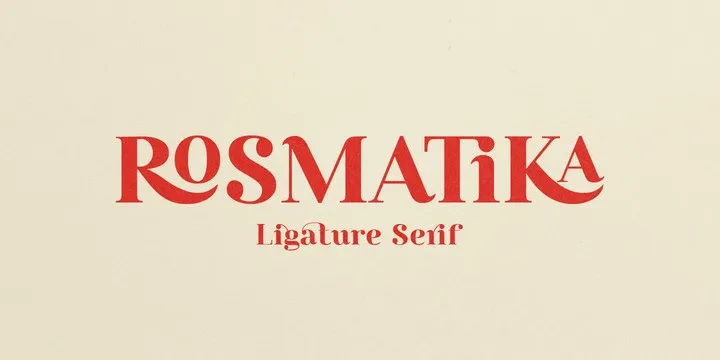
Rosmatika Serif Font Family – Download Grátis
Olá, amigos! Estou aqui uma fonte moderna inspirada em serif clássico, projetada para logotipos, identidades e materiais de edição. Inspirado na perfeição do equilíbrio entre energia dinâmica e beleza organizacional. Introduzimos a Rosmatika Fonte, uma Didone Serif contemporânea com muitas ligaturas. Essa é uma fonte para exibição com alta contraste que é adequada para uso em projetos de identidade visual, logotipos, designs de casamentos, postagens nas redes sociais, embalagens e etiquetas, marcações d’água, convites, anúncios e projetos que exigem fontes brilhantes e leves de ler. A Rosmatika tem mais de 500 caracteres para suportar a língua latina extensiva e inclui recursos como ligaturas padrão e alternativas específicas de idioma, bem como formas manuais personalizadas. Essa fonte é perfeita para quem busca um equilíbrio harmonioso entre design moderno e elegância clássica.